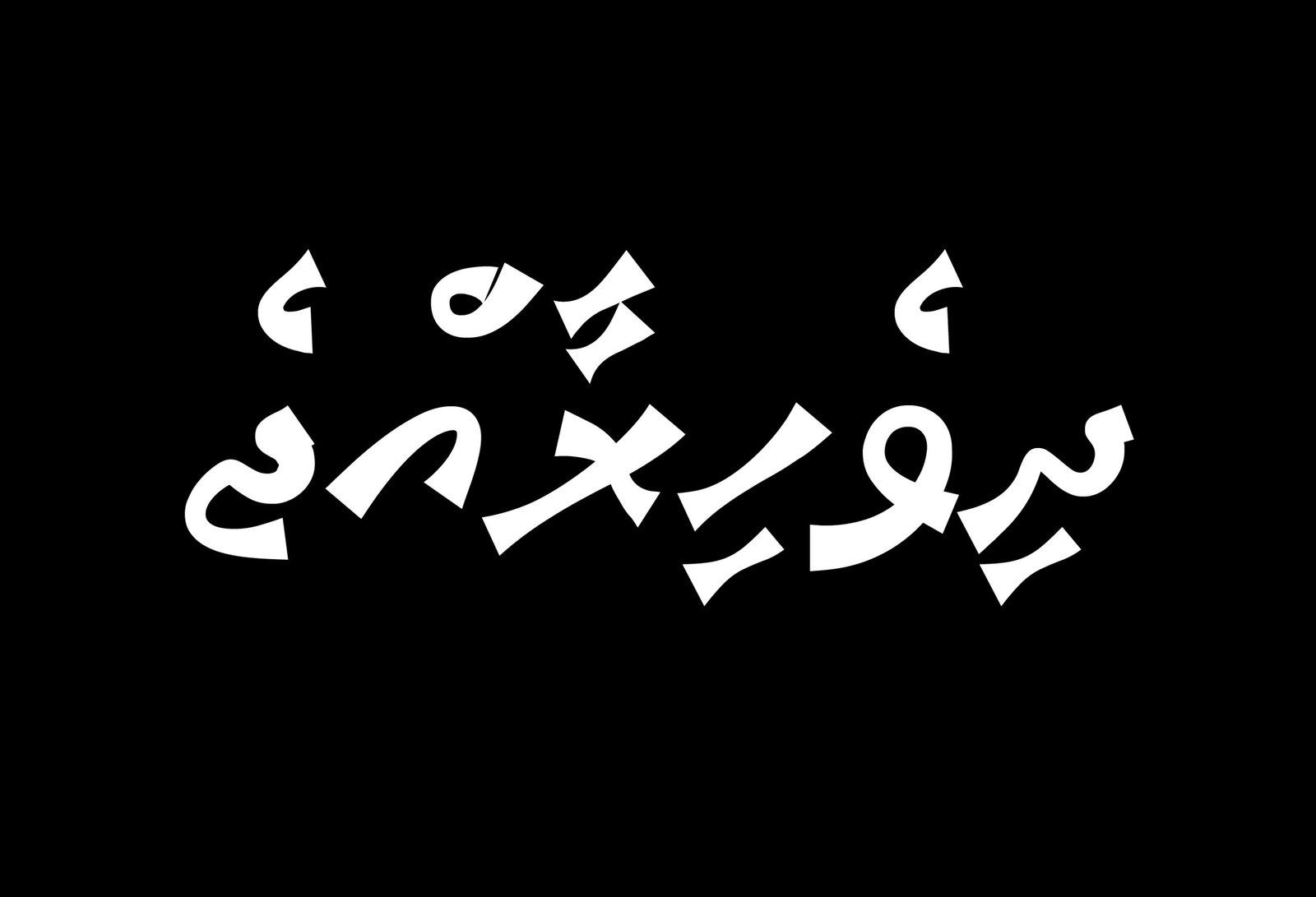
އެމްވީ އިޒްޔަން އެޖް
ެއިޒްޔަން އެޖް އަކީ އަކުރު ތަކުގެ ދެކޮޅު ވައް ނުކޮށް ތަފާތު ކޮށް ފަރުމާ ކޮށްފައިވާ ފޮންޓެކެވެ. މިއީ ޑިޖިޓަލް އަދި ޕްރިންޓް މީޑިއާ އަދި ކުޑަ ކުދިންގެ ހަފްލާ ތަކުގައިވެސް ބޭނުން ކުރެވޭނެ ފޮންޓެކެވެ. ފަރުމާކޮށްފައިވާ ފޮންޓެކެވެ.
“އެޖް” (Edge) ކިޔަނީ ކީއްވެ؟
“އެޖް” މި ނަމުން ދެވުނީ ކޮންމެ އަކުރެއްގެ ކޮޅު ކަނޑާފައި ފަރުމާކޮށްފައިވާ ގޮތަށް ބަލާފައެވެ.
ބޭނުންކުރަން އެންމެ ރަނގަޅު ގޮތްތައް
މިއީ ދިގު ލިޔުންތަކަށް ވުރެ ބޮޑަށް، ކުރު އަދި ފާހަގަކޮށްލެވޭ ސުރުޚީތަކަށް އެންމެ އެކަށީގެންވާ ފޮންޓެވެ.
ބޭނުންކުރާނެ ތަންތަން:
- ފޮތުގެ ބޭރުގަނޑު : ވާހަކަ ފޮތްތަކާއި ޒަމާނީ ފޮތްތަކުގެ ބޭރުގަނޑަށް ވަރުގަދަ ސިފައެއް ގެނެސްދެއެވެ.
- ބޮޑެތި ސުރުޚީތައް:ޕޯސްޓަރުތަކާއި، މަޖައްލާތަކުގެ ސުރުޚީތަކަށް ބޭނުންކުރަން ވަރަށް ރަނގަޅުވާނެއެވެ.
- ޑިޖިޓަލް ބެނާތައް: ވެބްސައިޓްތަކާއި ޑިޖިޓަލް އިޝްތިހާރުތަކަށް ސާފުކަން ގެނެސްދެއެވެ.
- ބްރޭންޑިންގ އަދި ލޯގޯ: ޒަމާނީ ބްރޭންޑްތަކާއި ކުންފުނިތަކުގެ ލޯގޯތަކަށް ސާފު އަދި ފާހަގަކޮށްލެވޭ ސިފައެއް ގެނެސްދެއެވެ.